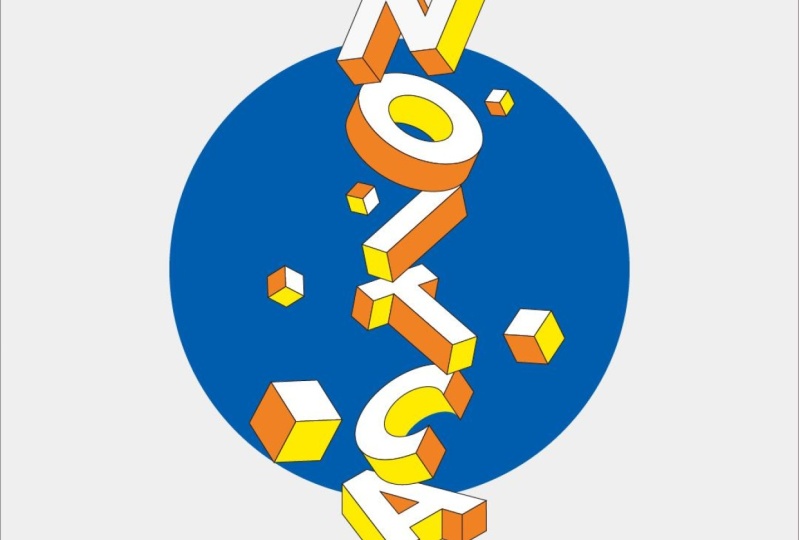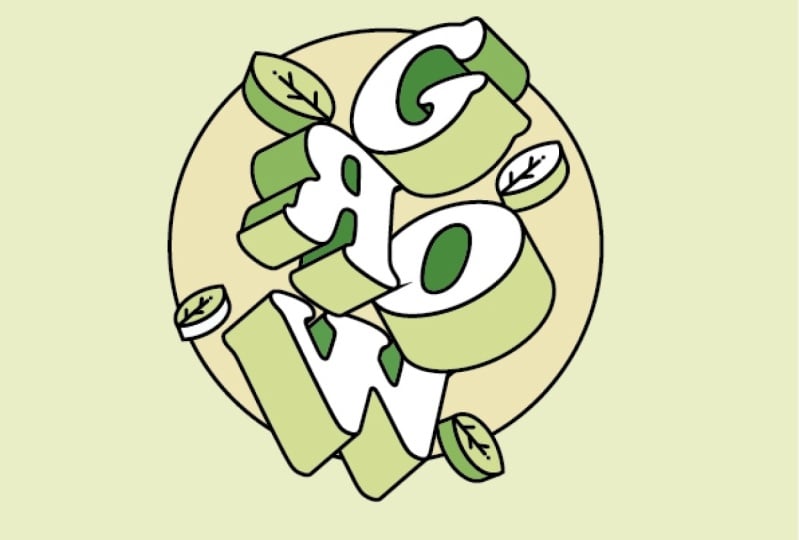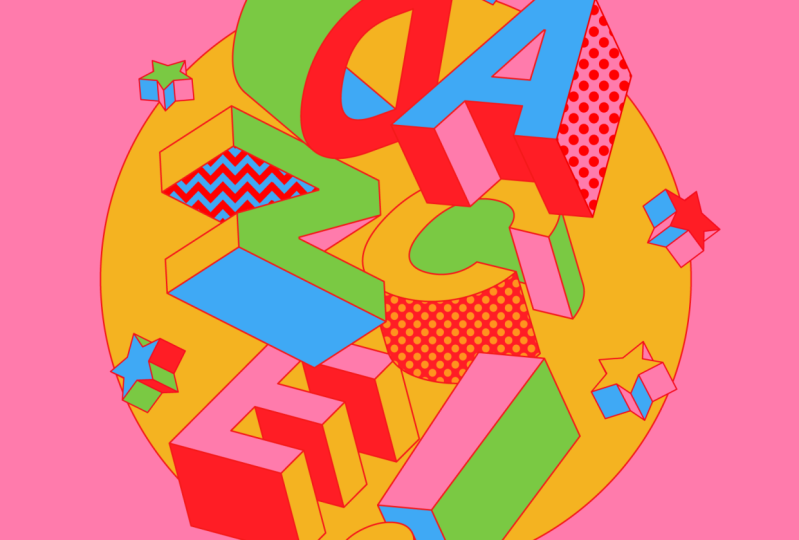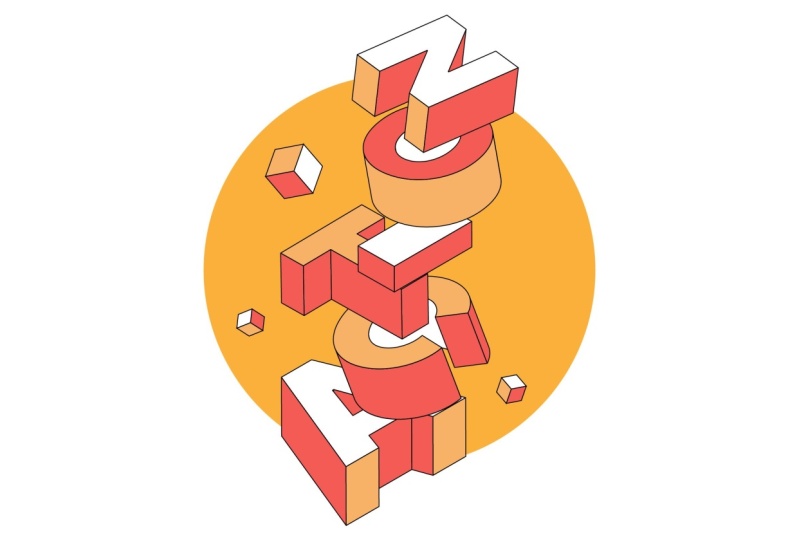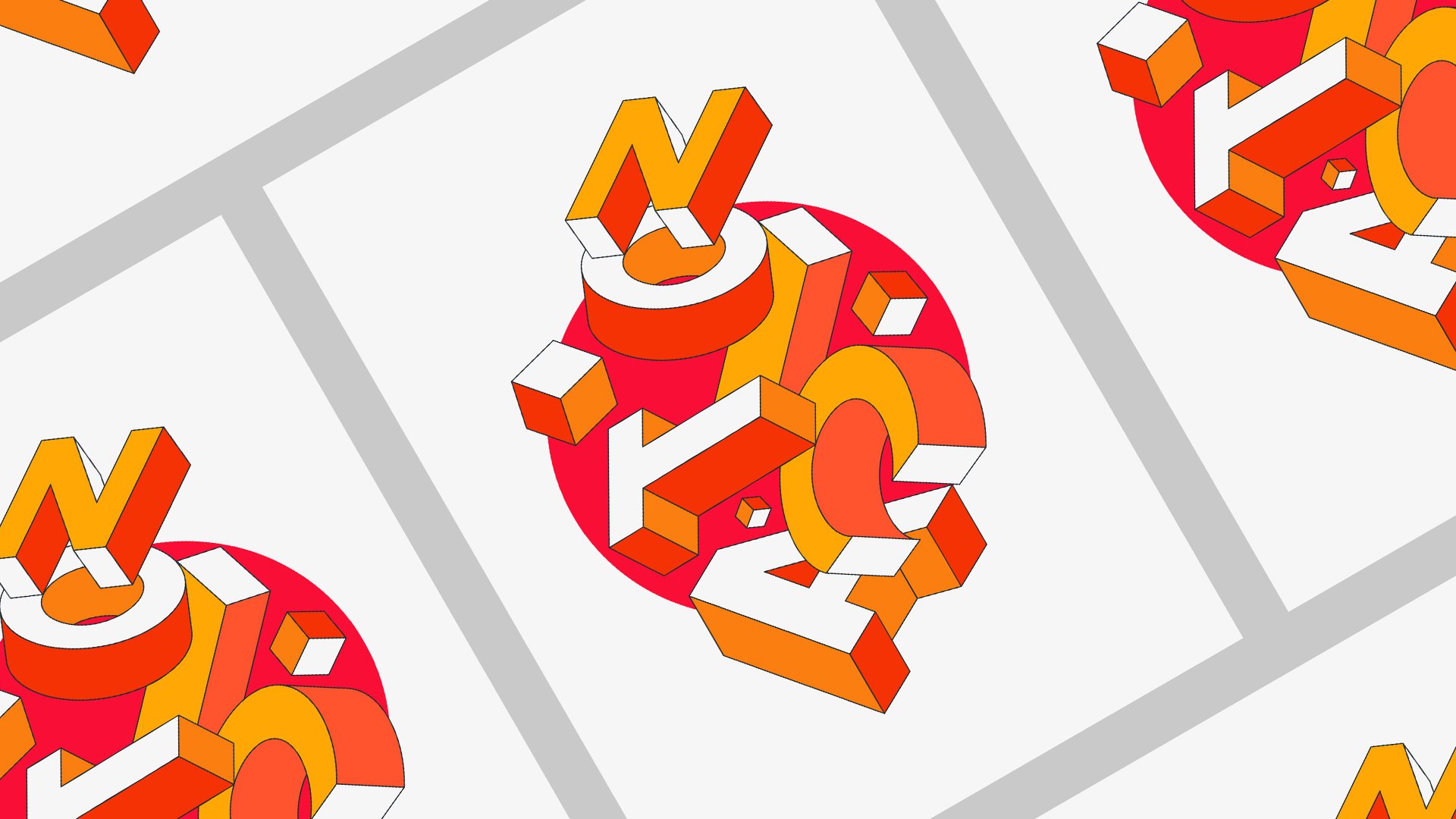
Aprenda em 10 - Ilustração de tipografia dinâmica
Aprenda em 10 ilustração de tipografia dinâmica
Aprenda em 10 é uma série de cursos curtos projetados para compartilhar ótimas técnicas em um curto espaço de tempo.
Neste curso, você vai aprender como criar uma ilustração de tipografia dinâmica no Adobe Illustrator e para isso, vamos aprender coisas como
• Como configurar nosso documento
• Como pesquisar fontes
• Como usar a ferramenta de extrusão em 3D no Adobe Illustrator
• Como trabalhar com a ferramenta Pathfinder
• Criar composições dinâmicas
• Use cores e contraste para melhorar o interesse em seus projetos
Isto é para todos! Especialmente pessoas que gostam de projetar com tipografia e criar composições dinâmicas
É perfeito para uma pequena pausa e um exercício rápido e uma exploração em design.
1. Aprenda em 10 ilustração de tipografia dinâmica: Olá a todos. Meu nome é Marcus e sou designer e animador de Londres. E bem-vindos à minha nova série de aulas, aprendendo dez, onde ensino grandes técnicas em dez minutos ou um pouco mais. Hoje, vou compartilhar com vocês como projetar essas ilustrações tipográficas. É um grande projeto e muito dinâmico. Vamos explorar as ferramentas 2D periféricas dentro do Adobe Illustrator e algumas maneiras muito legais de trabalhar com cores e composição. É uma aula curta, mas cheia de ótimas dicas e conhecimento. Você quer aprender algo realmente legal em 10 minutos? Cadastre-se agora e te vejo na aula. 2. Aula 01 — Projeto do curso e configuração de documentos: Olá a todos e bem-vindos a mais um aprendendo dez. Então, hoje nosso projeto de classe, estaremos projetando descartador. É principalmente topografia e há como uma tridimensionalidade aplicada a ela. Vamos aplicar isso usando alguns efeitos 3D no Illustrator, que serão muito fáceis e rápidos. Então, e então nós só vamos jogar com algumas cores quentes agradáveis aqui e criar uma composição agradável para trazer o significado da nossa ala em ação. Tipo, e ainda assim eu estava tentando fazer uma piada, mas, bem, sim, vamos fazer isso. Então a primeira coisa que precisamos fazer é realmente iniciar nosso documento. Então, se você estiver usando uma resolução 1080 por 1350, que é a resolução de postagem do Instagram. Normalmente eu só postar meus projetos pessoais e meus projetos de paixão no Instagram porque eles não são profissionais. Então, em um bom diagrama é uma ferramenta que eu uso mais para compartilhar meu trabalho. Então eu já coloquei como meu trabalho tomando uma resolução de água lá. Então é 1080 por 1350. E vamos pressionar Criar. 3. Aula 02 — Escolhendo sua palavra e fonte: Então a primeira coisa que eu vou usar a mesma palavra que eu usei antes, que era ação. E sim, eu uso a ferramenta de texto aqui. E eu vou selecionar dois, vou torná-lo um pouco como este. E na verdade não gosto desta fonte porque sim, este é Myriad Pro é a primeira fonte que ilustradores se aplica a você, mas você pode alterá-lo facilmente. Portanto, há várias maneiras de alterar sua fonte. Você pode simplesmente selecionar a fonte e ir para o menu aqui. E então você seleciona qual deles você deseja usar para este exercício. Você pode realmente entrar, usar como filtros e então você pode apenas tentar descobrir qual Bellefonte se aplica a você. Ou você pode realmente selecionar sua fonte aqui e clicar com o botão direito do mouse e ir para Fonte. E espere um pouco, porque você vai abrir. E então você pode realmente acessar toda a biblioteca de fontes aqui, que é Eleanor, ou às vezes é mais rápido e são, às vezes, se você sabe o nome da fonte, pode apenas digitá-lo lá. Então eu estou realmente indo para digitá-lo porque eu quero usar nós vamos usar a turnê de comida. Acho que havia aquele que eu usei para aquele exercício antes. Então, para atum é provavelmente já tê-lo em seu computador. Então, se você foi para a mesma conta de telefone, por favor, sinta-se à vontade. Ou se você quiser ir a uma pesquisa na internet para outros telefones, jogando alguma perspectiva 2D. E para o efeito neste tempo. 4. Aula 03 - Aplicando o efeito 3D: Tão fixe. Agora vamos aplicar um pouco de 3D nesta tipografia. Então, a primeira coisa, vamos selecionar este mundo aqui. Vamos ao objeto e vamos para Expandir. Então, deste modo, deste mundo, não estaremos mais em quê? Assim que você fizer isso, você pode mudar o mundo. Então, tenha certeza. Este é o mundo com que ele foi trabalhar e imprensa. Ok, então eu acabei de selecionar, arrastá-lo para baixo e vamos para Effect, e vamos para 3D, Extrude e Bisel. Na verdade, primeiro vou transformar minhas cartas em branco. Você vai ver o porquê. Então é um amplo conhecimento é mudado lá nas amostras e eu estava para 3D Extrude e Bevel. O uso de ticker branco é porque o 3D vamos usar de luz. E se ele é o último é preto, a luz não vai afetá-lo. Então, e porque estamos usando y dois, você realmente pode ver o cinza agora porque as sombras e bem, nós não vamos usá-los, mas é melhor para referência. Então aqui nós temos que, nossas perspectivas você pode realmente mudar meu normalmente se você quiser, apenas experimentá-lo para uma perspectiva realmente agradável que nós queremos usar. Aqui você pode mudar a profundidade do grande Yuan gostava que sua extrusão fosse pequena. Vamos usar apenas 50. E aqui você pode brincar com luzes. Mas para este exercício, não vamos muito mais longe com isso. Então, na verdade, vamos para a rotação personalizada aqui, e vamos clicar em Tab. E isso vai usar topo isométrico, que colocará nossas letras na perspectiva isométrica. E vamos apenas pressionar Ok. E sim, este é o efeito 3D é feito. E esta é a mentora que realmente precisamos para o nosso exercício. Então, novamente, menos ir para objeto e expandir. Na próxima lição, vamos começar a ter um pouco de cor e brincar com a composição dessas letras. Nós vamos aplicar um pouco de rotação e escala e um pouco e ver como podemos fazer como uma composição realmente agradável usando esta palavra. Então eu vi a próxima lição. 5. Aula 04 — Cores e composição: Acho que a cor é a minha parte favorita de qualquer projeto. Vamos selecionar isso e vamos desagrupá-lo primeiro. Assim como este. E agora vamos encontrar a nossa cor. Vamos para Color Themes. Sim. Então, outras equipes coloridas mostra uma biblioteca de conjuntos de cores surpreendentes já. Você pode usar qualquer um destes ou você pode usar o seu próprio? Então você pode criar o seu próprio aqui, ou você pode simplesmente explorar e encontrar alguns realmente agradáveis. Então, para este exercício, eu estou realmente indo para usar um fora aqui para eu não girar duas horas para tentar decidir qual cor eu vou usar, que é normal. Só quero usar este aqui. Quero adicioná-lo às minhas amostras. E aqui eu queria encontrar as minhas amostras. Eles estão aqui. Então, como você pode ver aqui, aqui está nossa nova biblioteca que acabamos de receber do outro Explorer de qualidade. Então, agora vamos começar a aplicar algumas cores nessas fontes. Talvez eu apenas selecione isso e aplique uma cor, cor laranja selecionada primeiro, é claro. E para ser capaz de entender o último melhor estão subindo por alguma cor do traço também. Então eu vou apenas aplicar um branco. Assim como este. Sim. E C, vou usar uma cor diferente. Talvez você leia talvez uma laranja escura, na verdade. E eu vou aplicar um derrame em branco também. Então aqui precisamos realmente fazer algo em C aqui por causa do efeito 3D. Se GFS você criar mais formas. E a maneira como você pode resolver isso é realmente desmoronar suas naves juntos. Então vamos selecionar estas formas de homens aqui. E vamos para Pathfinder e basta clicar aqui, que irá adicionar todas as formas juntas. Você vai uni-los. Então, e novamente, a mesma coisa aqui. Una-os. E sim, perfeito, sem problemas. Agora, vamos selecionar T e apenas copiar a cor de a. seleciona. Eu chamo de copiar as cores para ter certeza que é um grupo. Estou usando a ferramenta conta-gotas só para pegar as cores de outras letras. E é uma maneira mais rápida do que selecionar o canto direito silencioso. Faça a mesma coisa aqui na uni-los e uni-los novamente. Ou há algo lá. É que cada vez que fazemos isso começará a apresentar um resultado diferente. Então, sim, provavelmente é quando eles são as mesmas formas que eu. Se você está usando palavras diferentes, mas ação, e eu vou usar e escrever isso. Bem, deixe-me apenas verificar novamente as áreas das colunas usando ok. Sim, faz com que esteja tudo bem por enquanto. Então a próxima coisa que vamos fazer agora é jogar um pouco. Como você vai compor essa cena? Então vamos arrastar o A para o meio. Vamos selecioná-lo. E isso é apenas refletido, Oh meu Deus, aqui está verticalmente, então você tem que mudar a orientação do a. Você pode selecionar recentemente verticalmente ou você pode escolher seu próprio ângulo. Neste caso, vamos usar um vertical e pressione Ok. E eu vou deixá-lo aqui, vou pegar C e ir talvez. Agora vamos manter as mesmas escalas. Vou sair daqui, vou buscar o chá. Quero dizer, nós fizemos. Ela realmente foi para refere-se a reflexão, bem como para vertical. Então você precisa ser, você precisa ser capaz de lê-lo, você sabe, assim estar ciente de em seu computador. Você pode perder o significado da palavra que você está tentando retratá-la e ilustrar. E agora vou selecioná-los todos assim. E eu vou escalá-lo um pouco assim. Perfeito. E talvez eu vá me centrar em você, todos que são ferramentas alinhadas aqui. Só por agora. Vamos começar a brincar com um pouco de rotação. Selecione a forma e pressione R. A possibilidade de rotação, possibilidades acontecem. Então você só começa a ser capaz de girar isso como quiser. Então eu vou girar E, aluno girado t para fazer algo um pouco mais dinâmico. E jogue um pouco com a posição das letras. Assim, a ação não pode girar. Oh, talvez desse jeito. Porque o OH vem depois e depois n. Sim, algo mais como isso. Talvez até possa jogar um pouco com escala se eu apenas selecionei e, em seguida, pressione E. Você realmente me deixa brincar com escala para que você possa realmente adicionar Lei, um pouco mais de perspectiva na cena. E sim, e a próxima coisa que vamos fazer é realmente mudar algumas cores aqui. Vou fazer estes largos. E este branco também. Só muda os núcleos aqui. Então há mais contraste e que nós realmente podemos entender um pouco melhor. E aqui vou eu, estou apenas clicando duas vezes sobre o grupo e então eu posso selecionar as formas aqui. Eu vou adicionar um pouco dessa cor mais escura como simular um tipo de afirmação. Eu peguei uma espécie de sombra. Se você, se isso faz sentido. Na verdade, melhor, vou usar como símbolo do exercício. Eu vou fazer os traços escuros assim, para que não haja correspondência perfeita com eles. Então você vai ficar preto também. Sim. Perfeito, algo assim seria incrível. E agora vamos apenas mudar adicionando algumas cores diferentes aqui para simular talvez um pouco de vôo. Neste caso. Vamos usar a mesma cor. E vamos fazer o mesmo para estes últimos um como este. E é o mesmo aqui. Talvez você vá realmente usar alguns brancos também para fazer algumas cenas mais leves. O importante aqui é tentar adicionar um pouco mais de detalhes na ilustração. Como se houvesse como lançar sombras ou até mesmo um pouco de como sombras falsas, principalmente exatas. Alguém pintou. Na verdade, não significa ser exatamente uma sombra respeitando seu ponto de luz ou domingo. Então vamos apenas selecionar este e este, vamos torná-lo vermelho assim. E aqui estamos um problema porque há um vermelho também. Talvez na verdade usamos ou a cor para um aqui e B é laranja e usamos raramente dentro. Como este. Sim, já está muito bonito. E eu vou usar laranja aqui. Vermelho seria bom, seria, o n será branco, então, que terá de fazer, ver branco também. Então sim, algo assim. Você pode realmente jogar um pouco mais com as sombras e as cores que você não precisa. Você pode usar mais cores se quiser. Seja totalmente livre com ele. Vou parar com isso agora, porque não quero fazer isso um pouco mais. E eu acredito que você pode fazer o resto sem muita bondade agora. Então, na próxima lição, vamos ter um pouco mais de detalhes. Nós não adicionamos um pouco de fundo na cena e um pouco de mais elementos apenas para levar um pouco mais de história para a cena. Então eu vejo na próxima lição. 6. Aula 05 — Edições finais e detalhes: Olá a todos. E espero que todos estejam se divertindo fazendo exercício. Então agora vamos apenas fazer um pouco de detalhes e apenas terminar isso. Então, estamos prontos para o próximo curso. Então, a primeira coisa, vamos usar nossa ferramenta de retângulo aqui. E vamos arrastá-lo até a partir do canto. A menos que tivesse como uma cor acinzentada, ou poderia ser totalmente branco também. A coisa sobre a cor acinzentada é como se você diferenciasse do branco na letra, que é, é ótimo para cabeça um pouco mais de profundidade. Agora, talvez eu queira torná-lo um pouco mais claro cinza. Não, eu não acho que eu vou fazer para nós essas ilhotas com elipsoidal, um pequeno círculo atrás. E vamos torná-lo talvez um vermelho escuro. E eu vou apenas clicar com o botão direito sobre ele, Transformar, Organizar, Enviar para trás. Então, na verdade, vamos apenas enviar para o saco e, em seguida, selecionar o fundo. Envie o fundo para a parte de trás. E talvez vamos apenas mudar para um correlato cria um pouco mais de contraste. Deixe-me rolar até aqui para explorar algumas opções, a fim de me apegar para entreter. Então vamos deixar assim ou corrigir. C já está muito bonito. Eu realmente gosto desse tipo de composição dinâmica acontecendo aqui. Eu acho que é realmente, é realmente interessante que você sinta que eles estão dois acima como a escalada um no outro. E eu não sei, eu sinto, eu sinto que é tão interessante quando você pode realmente ver o primeiro vislumbre. Você vê o o é uma boa ilustração, mas então você realmente entende que é como se outra coisa também fosse uma palavra que, que poderia ser como seu manifesto ou como ação para sua vida. Ou, sei lá, algo inspirador. Eu acho que nos dias de hoje um monte de potencial nesta técnica. E eu vou entrar em um pouco de detalhes. E agora vamos usar uma ferramenta de retângulo novamente. E eu vou desenhar um pequeno círculo, pequenos retângulos, desculpe, quadrado. E eu vou pegar esses números aqui, vou fazer 55 para ser como um número exato. Mesmo uma cópia disso, Eu vou remover o acidente vascular cerebral e eu vou tratar a Extrude e Bevel novamente. Mas aqui vou usar um 55 aqui para fazer um cubo perfeito. Vamos pressionar “Ok”. Na verdade, vamos voltar. Precisamos, precisamos de nossos atributos aqui, e vamos para um ponto. E eu seleciono aqui, desculpe, eu só tenho muitas janelas acontecendo agora na minha tela. Certo, vamos aos atributos. botão direito do mouse e vamos mudar sua perspectiva para topo isométrico também. E pressione Ok, Vamos para o objeto, expandir a aparência. E vamos. Então agora vamos, agora selecione essas formas também. Vamos roubar as cores a partir de agora as letras como esta. E, no entanto, agora temos um cubo que podemos realmente adicionar à nossa ilustração. E girado fabricante tinha um pouco mais de detalhes, escalá-lo para cima e para baixo. A idéia é apenas levar um pouco de visual mais interessante sobre ele. Então, como alguns quarteirões aqui e ar, talvez com direções diferentes e algo assim. - Sim. - Sim. Eu não queria parar aqui. Vou deixar você brincar com isso agora. Eu acho que, por favor, certifique-se de fazer o exercício, o exercício da aula, ou realmente quero ver o que vocês vêm para cima também. Mais uma vez, sinto muito por não poder fazer essas aulas em dez minutos. Notei que é impossível ensinar um dia em design em dez minutos. E bem, se você gostou desta aula, por favor, me dê um acompanhamento. Me deixe um comentário sobre uma aula e faça o exercício. Adoro ver o que vocês desenham o tempo todo. E, por favor, não hesite em contactar-me no Facebook ou num Instagram, seja qual for o meu perfil. Então, sim, estou aqui para ajudar. Tenha um bom dia. Tchau-tchau.